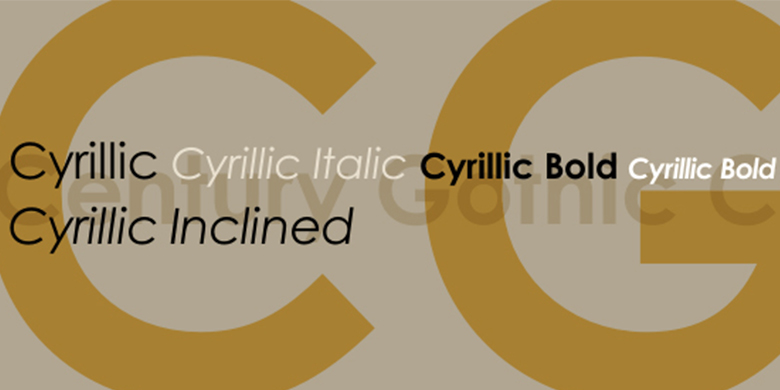
Century Gothic™ Cyrillic
Century Gothic™ Cyrillic,这款字体结构工整、笔画清晰,兼顾美观与易读性,适用于标题、正文、海报、包装、LOGO 等多种场景。字形优雅稳定,风格百搭耐看,适配日常排版与创意设计,让文字呈现更舒适、更具质感。Century Gothic™ Cyrillic一笔一画,皆是细节,以均衡的比例、流畅的线条打造舒适视觉体验,字形端正大气,风格简约现代。无论是商业设计、品牌宣传还是日常排版,都能轻松驾驭,让文字更有格调与力量。Century Gothic™ Cyrillic字体下载。
字体品牌: Monotype 设计师:Sol,Hess,Monotype 字体分类:无衬线体 字体属性:外文 字符集:Unicode 发布时间: 2009